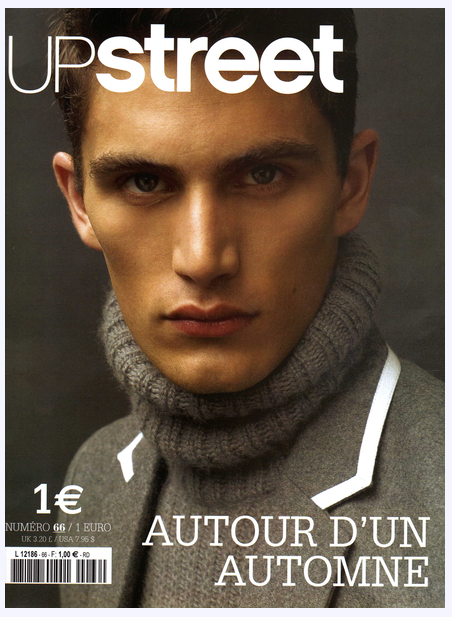
Das sieht sehr konstruiert aus … ein bisschen Helvetica (s), ein bisschen Museo Sans (t), ein bisschen Mason Demi (e). Fraglich ob das überhaupt ein Font ist.
"Chalet"